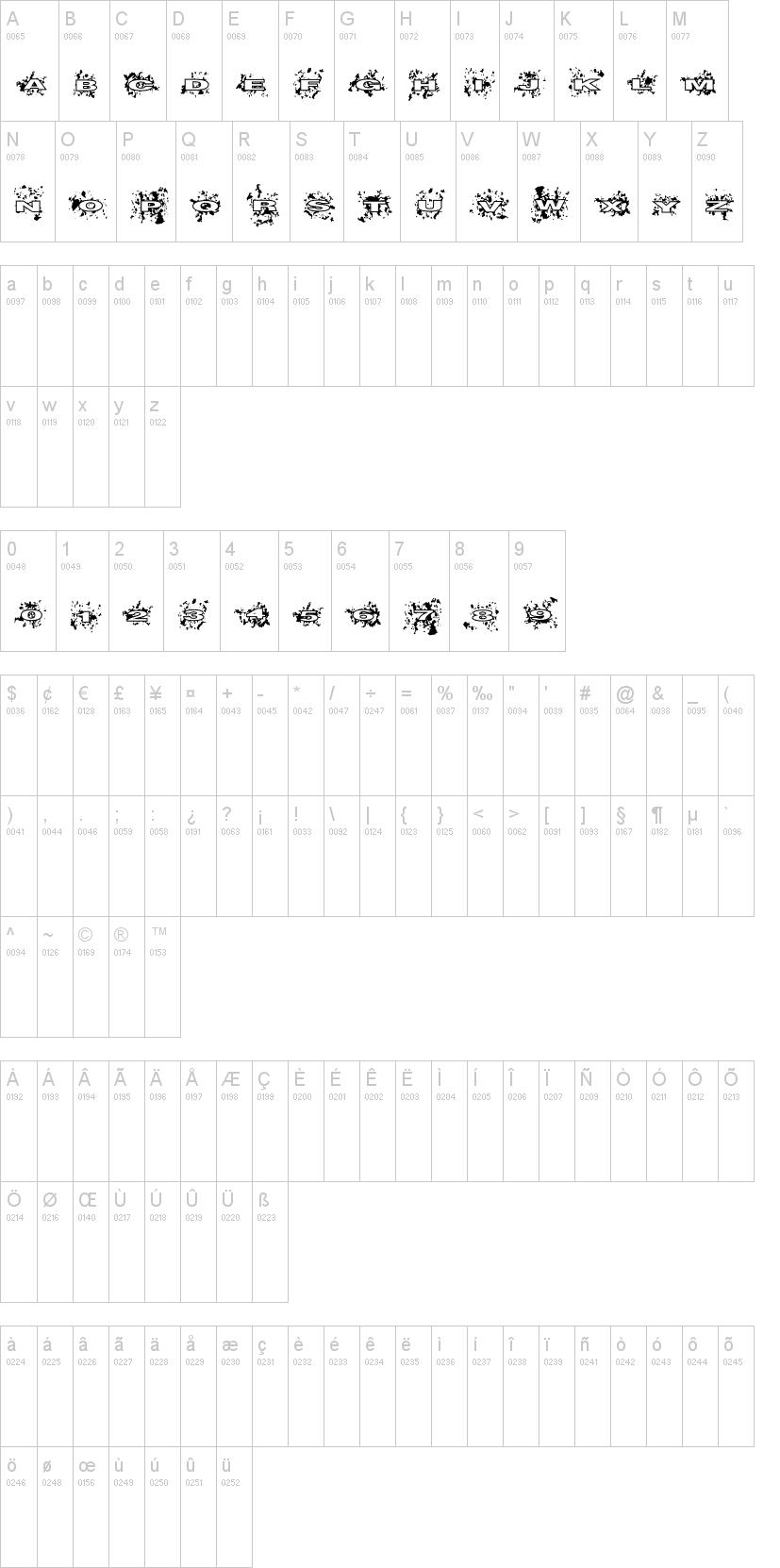
Splatish
Splatish 是一款字体,由著名设计师Mikko Nuuttila设计,它的特点是十分复古而又有趣,它的字体形状有点像涂抹式的,有点像涂抹画,给人一种放松的感觉。它的字体也有很多种,从清新的简约风到复古的风格,都能够满足不同的需求。
Splatish是一款非常不错的手写艺术字体,具有很好的视觉感,适合于文化类的宣传设计、商业类品牌的广告和产品包装设计以及个性化文字排版等较多场景。